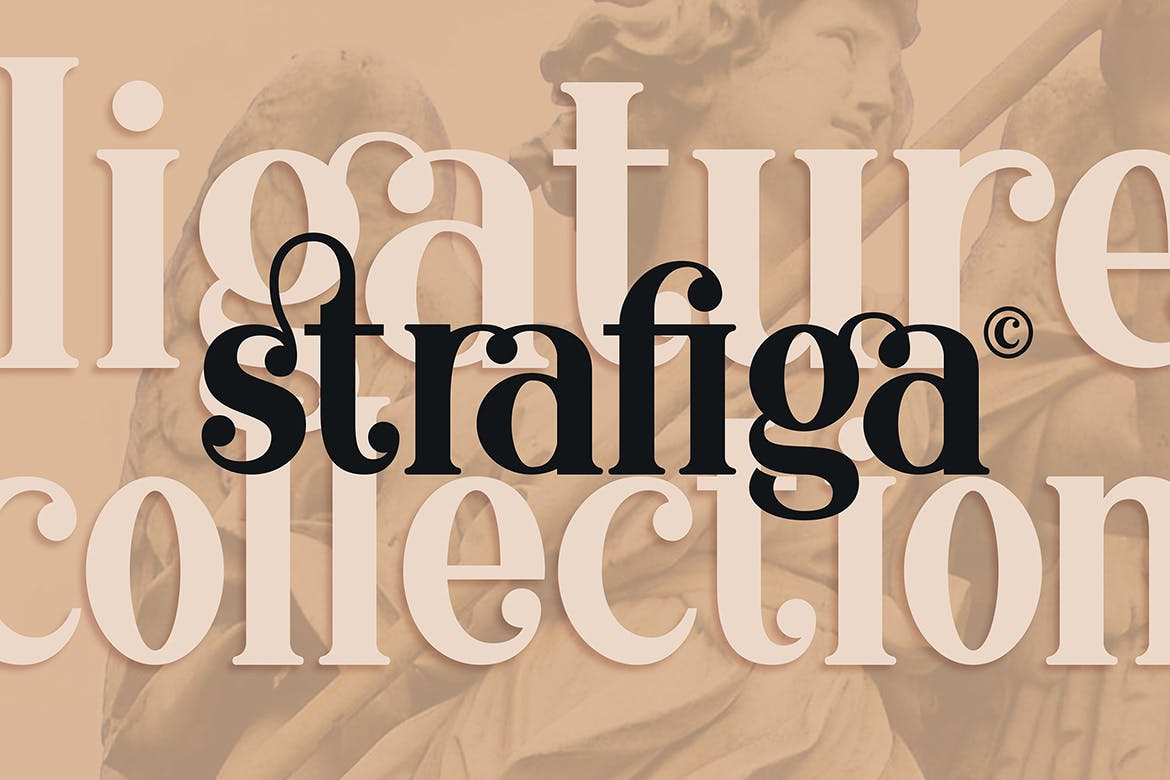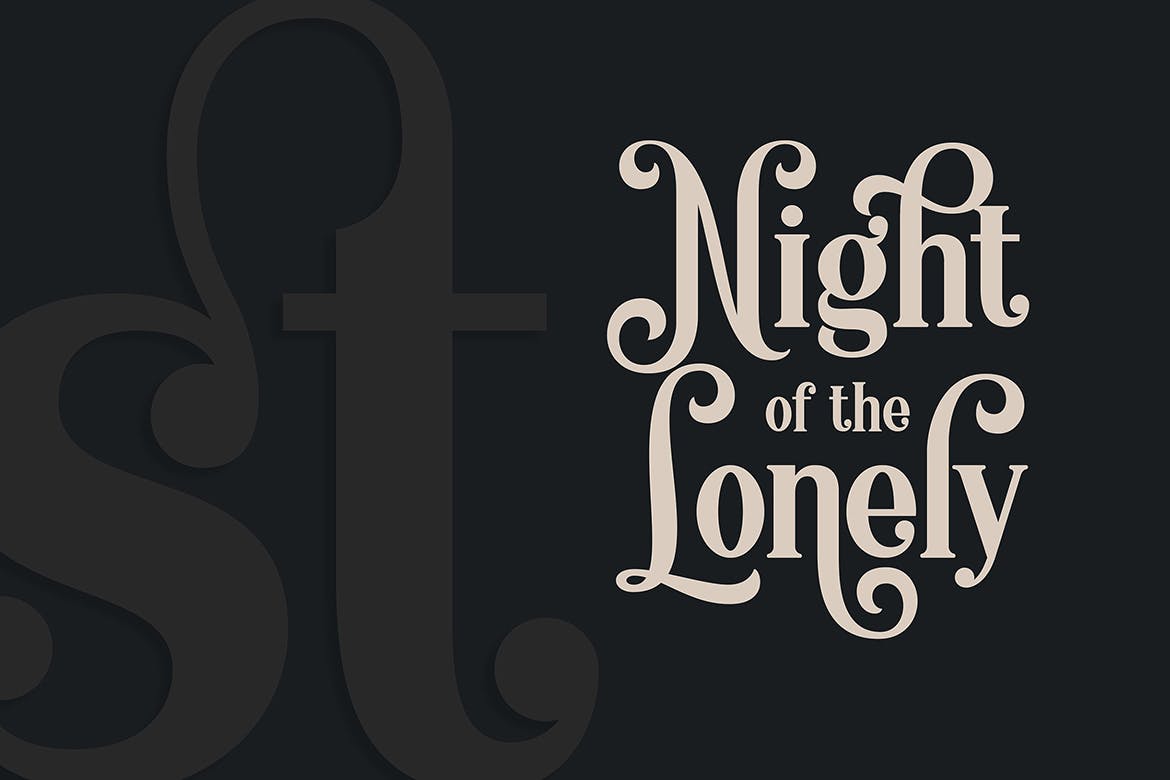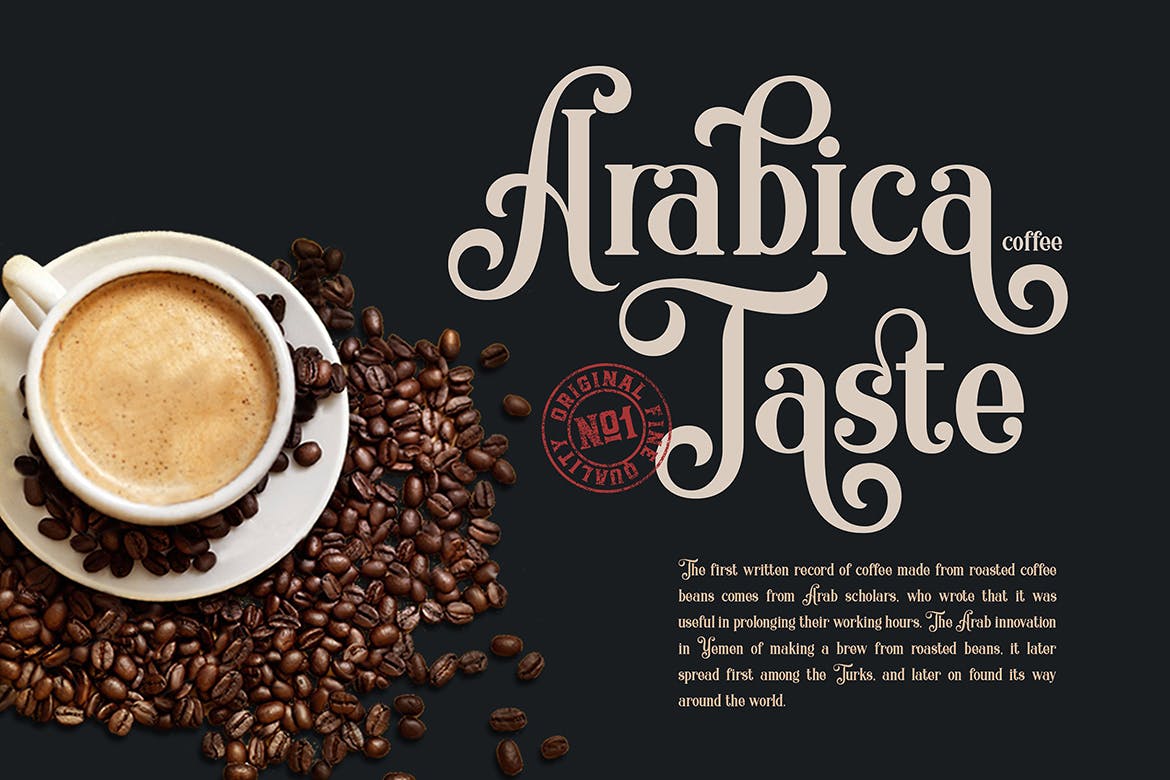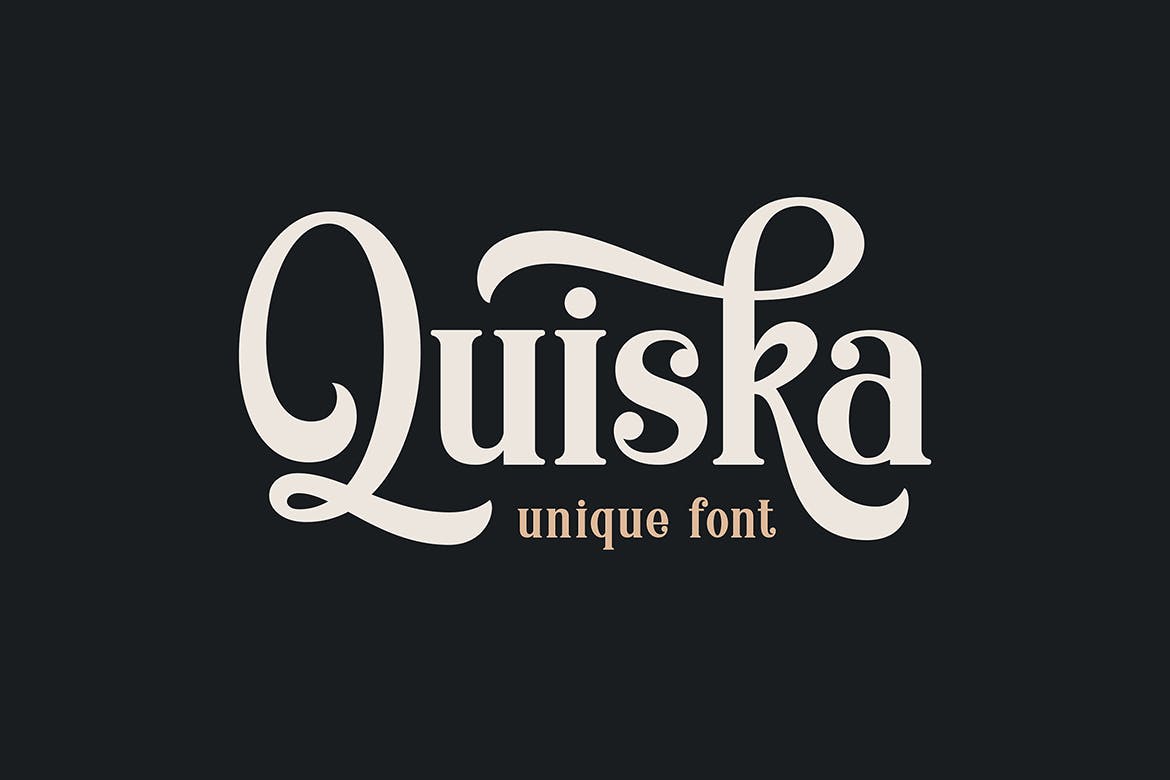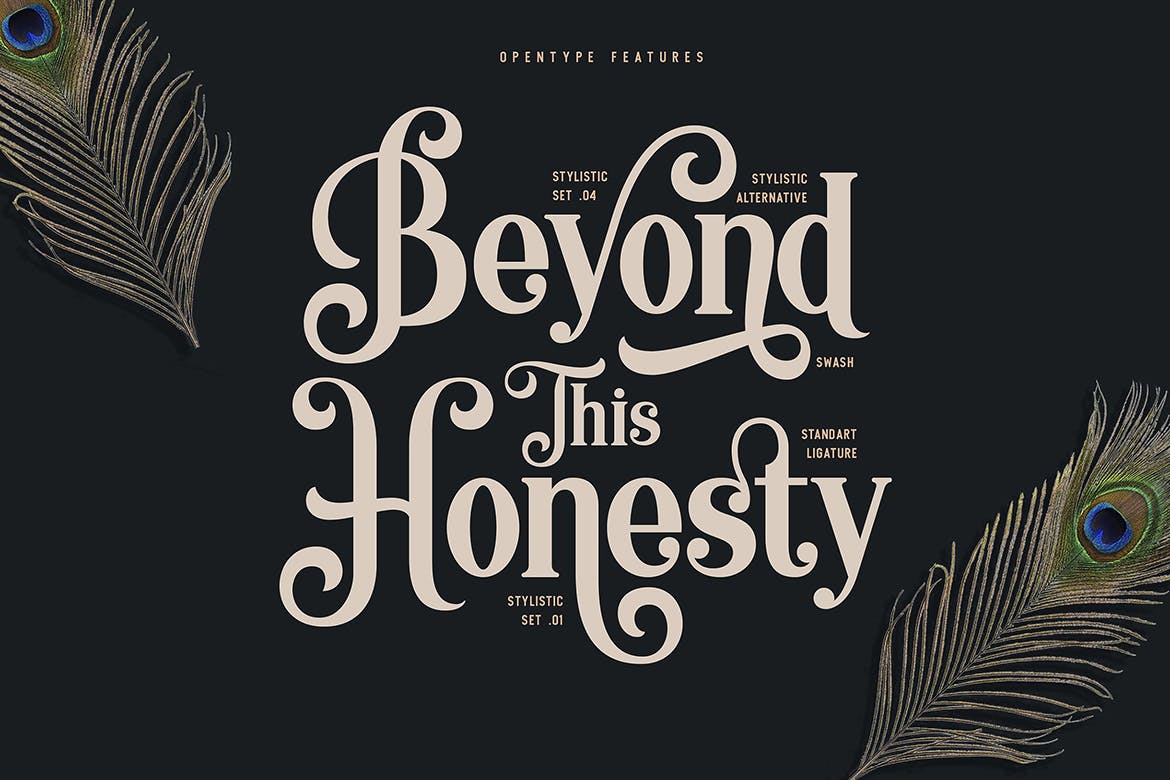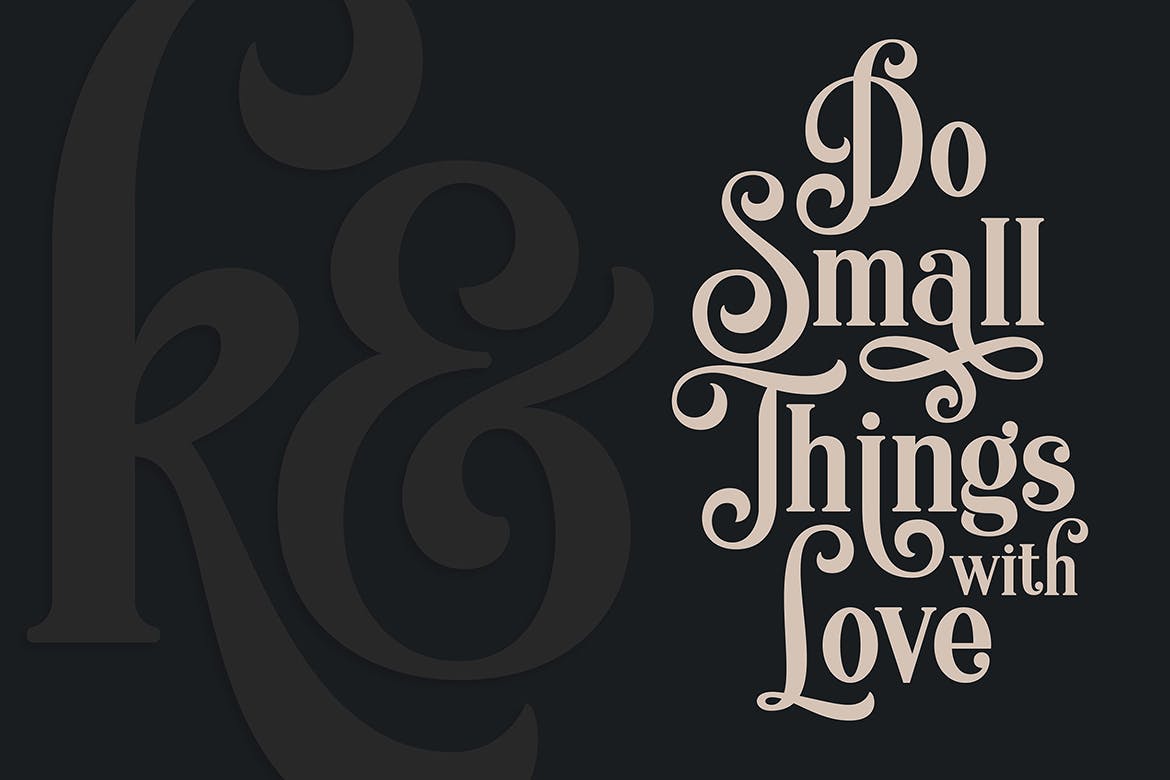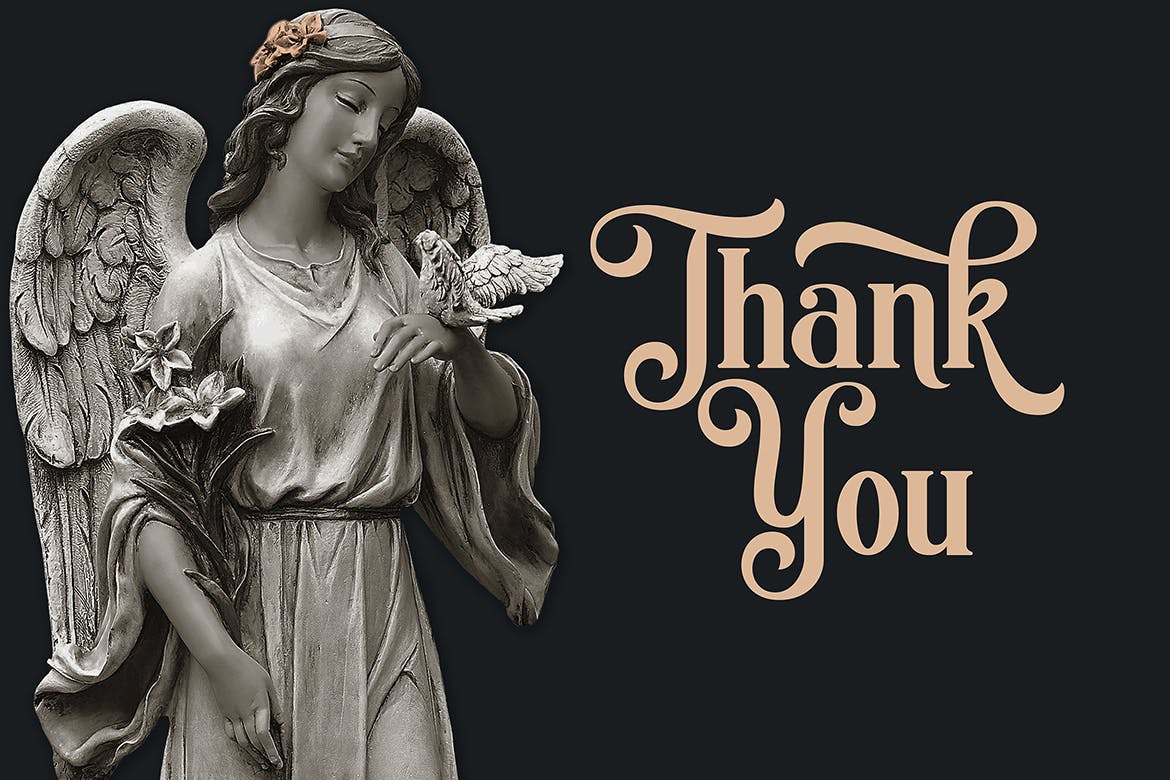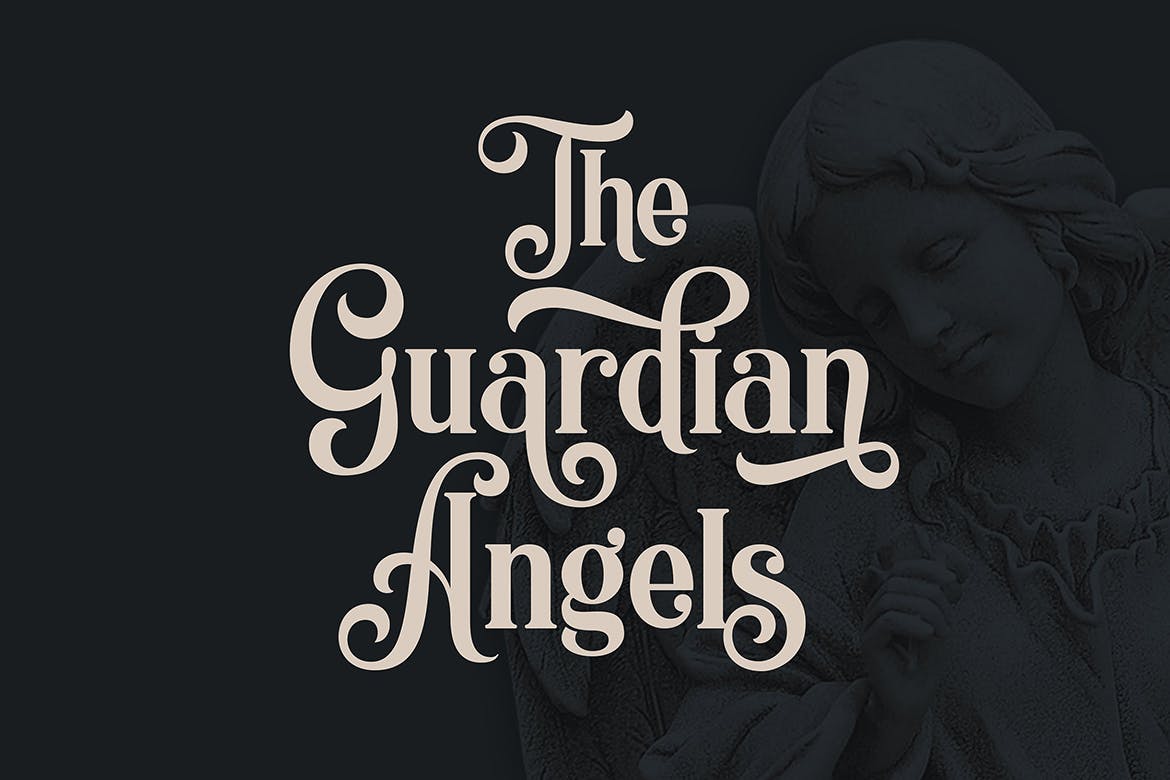
فونت Quiska یک فونت سریف منحصر به فرد است که با ترکیب حروف بزرگ خاص و کاراکترهای جایگزین زیبا همراه با شکلی جذاب ارائه میشود. این فونت دارای بیش از ۳۰۰ گلیف میباشد و میتوانید از آن در طراحی لوگو، مدال، هنر تایپوگرافی، بستهبندی، عنوان، پوستر، تیشرت/پوشاک، کارت تبریک و دعوتنامههای عروسی استفاده کنید. همچنین میتوانید فونت Quiska را با مجموعهای از کاراکترهای جایگزین ترکیب کرده و به طرح خود جلوهای خاص ببخشید.
کاراکترهای جایگزین در این فونت به چندین ویژگی OpenType تقسیمبندی شدهاند، از جمله Alternates Stylistic، Sets Stylistic، Titling، Swash و Ligature. شما میتوانید به امکانات OpenType با استفاده از نرمافزارهایی مانند Adobe Illustrator، Adobe Photoshop و Adobe InDesign دسترسی پیدا کنید.